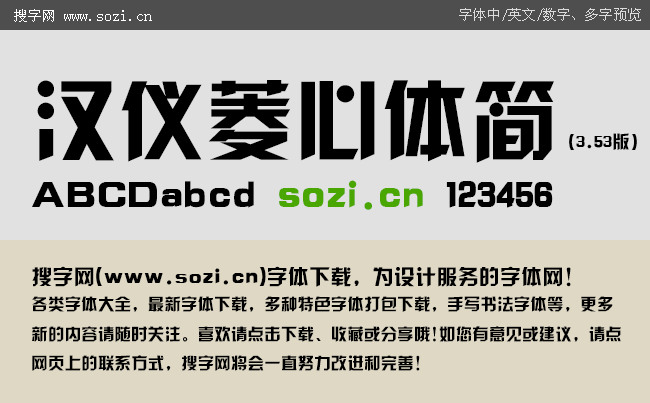
漢儀菱心體簡(jiǎn)3.53版
搜字網(wǎng)提供一款漢儀菱心體簡(jiǎn)中文藝術(shù)字體下載,漢儀菱心體簡(jiǎn)是一款筆畫粗壯、新穎獨(dú)特的藝術(shù)字體,該字體具有醒目、突出的視覺效果,適用于包裝印刷、廣告設(shè)計(jì)、平面設(shè)計(jì)、海報(bào)設(shè)計(jì)等領(lǐng)域。